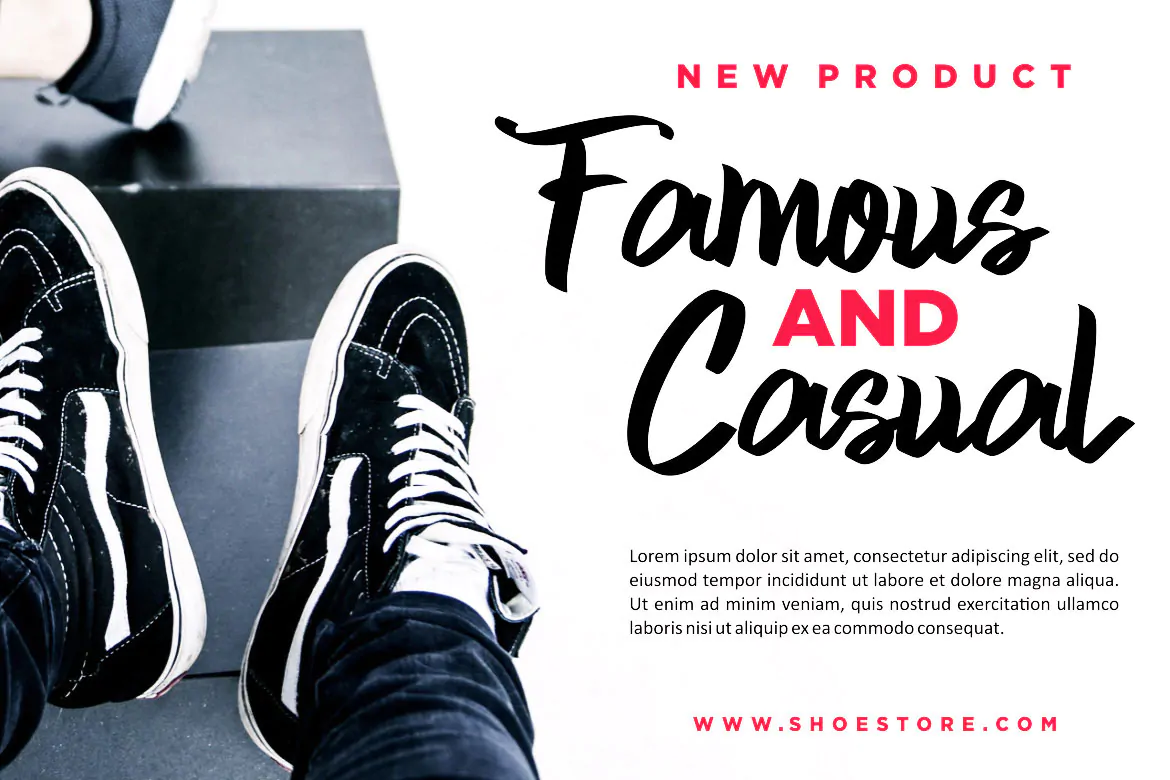
فونت مدرن و بولد Skid Rock
فونت مدرن و بولد انگلیسی
فونت مدرن و بولد Skid Rock یک اسکریپت فونت انگلیسی است که مناسب برای استفاده در طرح و پروژههای گرافیکی مختلف میباشد. این فونت زیبا با وزن معمولی طراحی شده است که میتوانید در طراحی پوستر، چاپ تیشرت، بسته بندی محصولات، ظروف کاغذی یکبار مصرف، لوازم التحریر و … استفاده کنید.